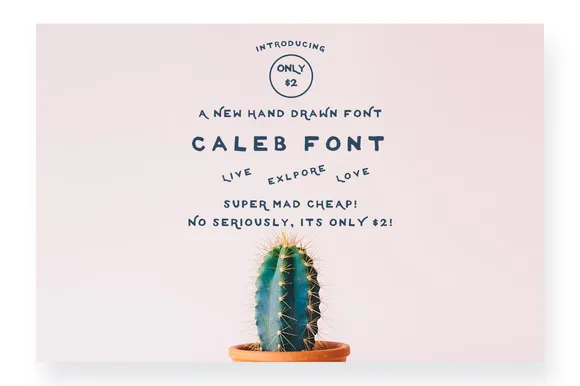
Caleb Font – Download Grátis
A Calebre é uma fonte tipográfica Display, cuidadosamente criada pelo Greenhouse Supply Co., conhecida por sua elegante escrita a mão. Embora tenha um design simples e básico, possui um toque único que o torna perfeitamente adequado para diversas aplicações. Ideal tanto para criar logotipos memoráveis quanto para cardes de casamento, cartazes e designs de roupas, esta fonte é uma opção versátil para designers de todos os tipos. Perfect para aqueles projetos que exigem um toque autêntico e personalizado. Não importa o que você planeja usar a Calebre, seja ele um design simples ou algo mais elaborado, ela está aqui para complementar seu trabalho. Aproveite esta fonte de qualidade para agregar ainda mais valor aos seus projetos.